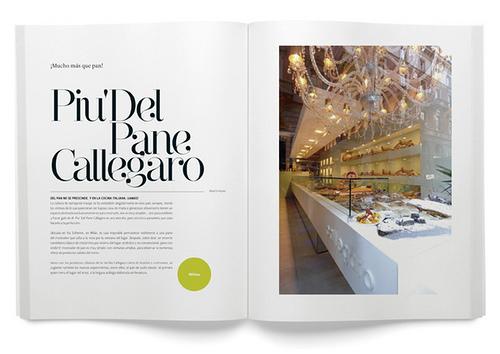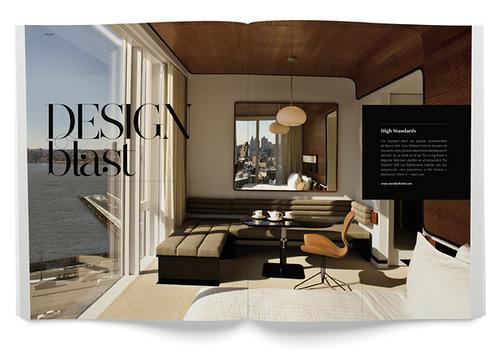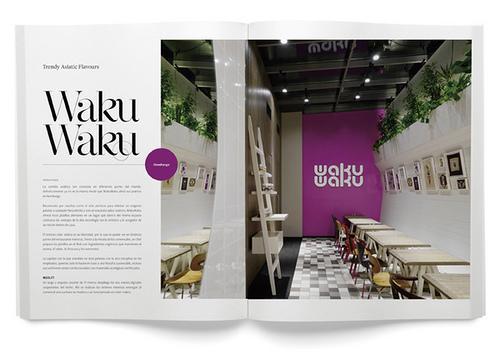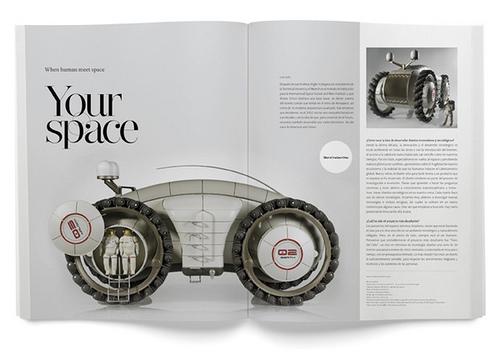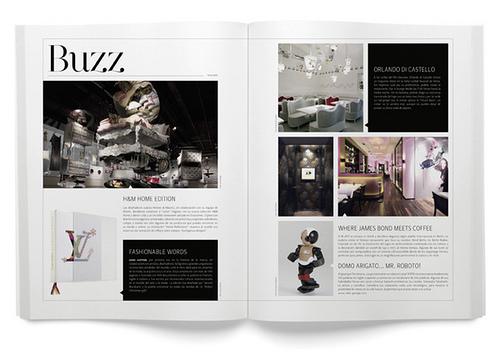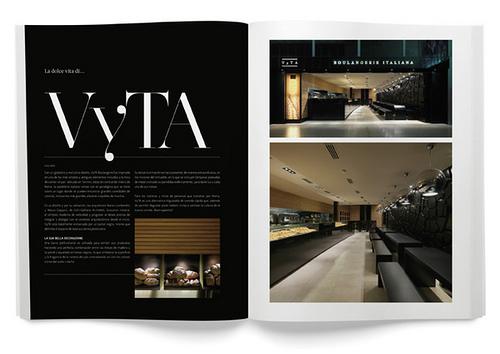
Freundliche Serifenschrift
Nachdem mein Dozent mir auch nicht helfen konnte wende ich mich nun an euch. Ich habe hier eine wunderschöne Schrift gefunden:
Gemeint ist natürlich immer die Überschrift. Ich wäre euch sehr dankbar, wenn ihr mir den Namen dieser Schrift sagen könntet.
Wie man allerdings ein Layout unverzerrt mit geraden Kanten in ein aufgeschlagenes Buch reinfaken kann ist mir ein Rätseln. Da müsste doch dem Grafiker die Maus aus der Hand fallen …
Hoffentlich ergibt sich bald ein Projekt, wo sie Anwendung finden kann.